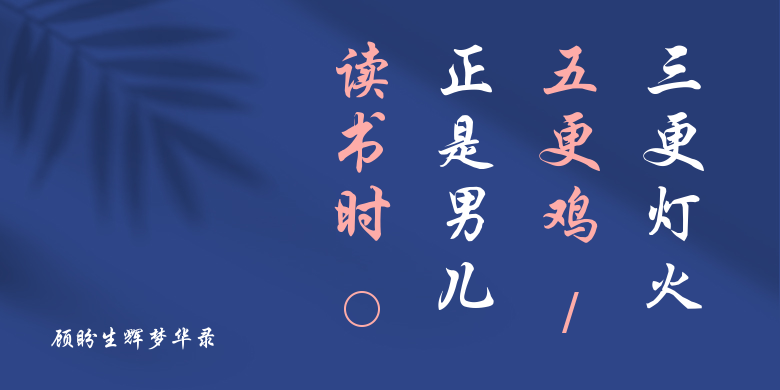
顾盼生辉梦华录,这款字体结构工整、笔画清晰,兼顾美观与易读性,适用于标题、正文、海报、包装、LOGO 等多种场景。字形优雅稳定,风格百搭耐看,适配日常排版与创意设计,让文字呈现更舒适、更具质感。顾盼生辉梦华录一笔一画,皆是细节,以均衡的比例、流畅的线条打造舒适视觉体验,字形端正大气,风格简约现代。无论是商业设计、品牌宣传还是日常排版,都能轻松驾驭,让文字更有格调与力量。顾盼生辉梦华录字体下载。